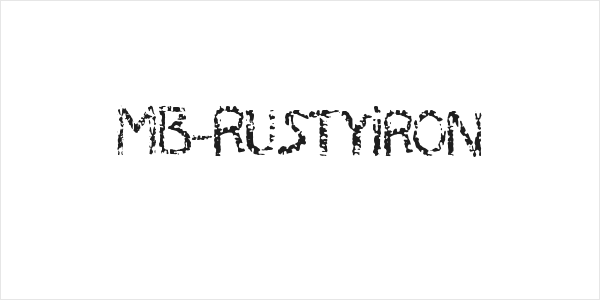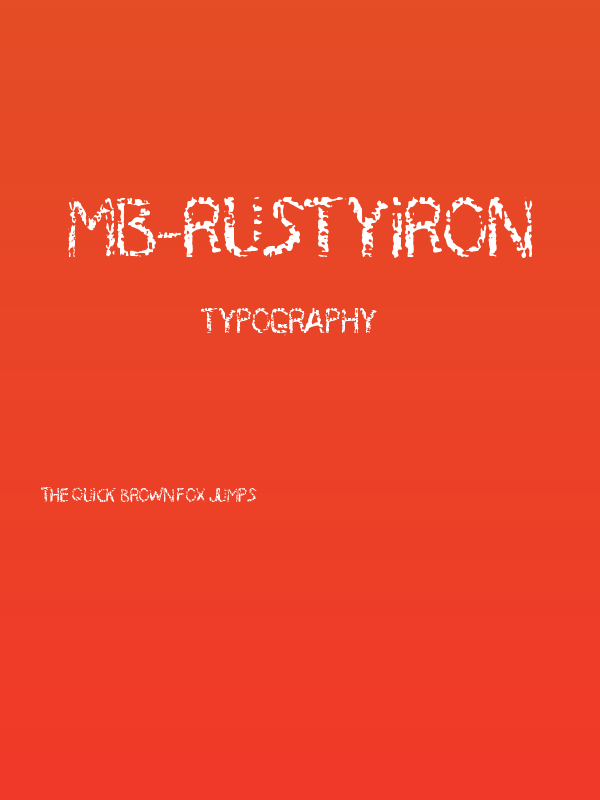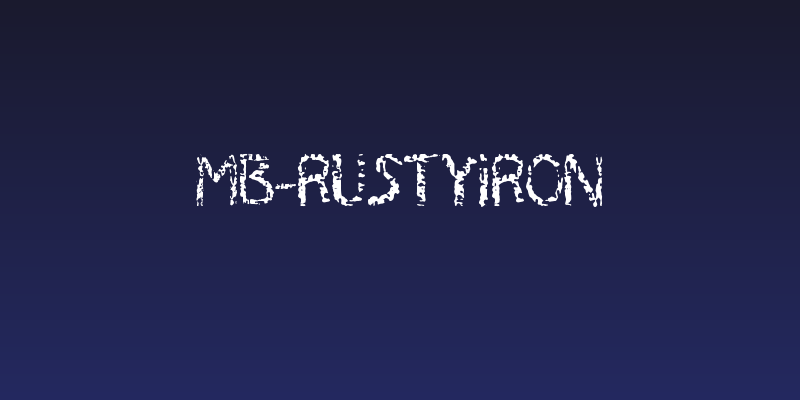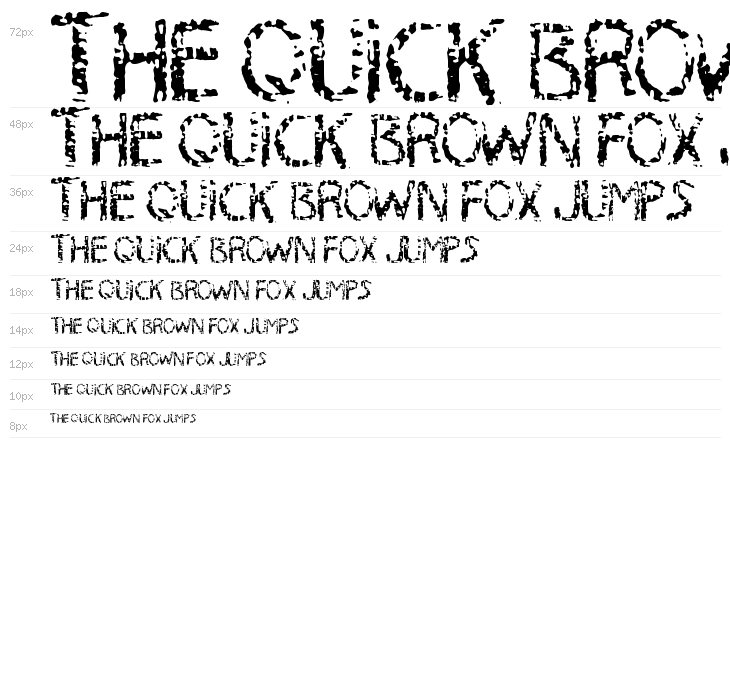
MB-RustyIron Font
✎ Distorted Eroded
| Progetti proposti | Ideal for vintage posters, industrial-themed designs, branding for rustic products, or any project needing a bold, aged look. |